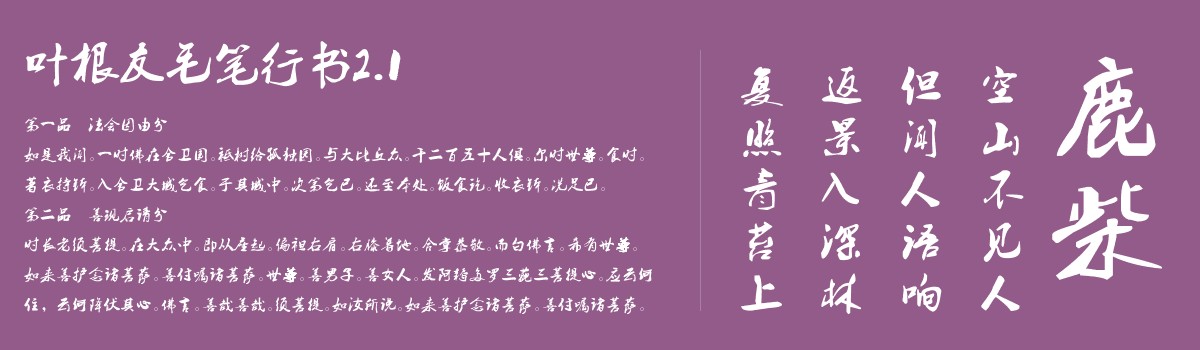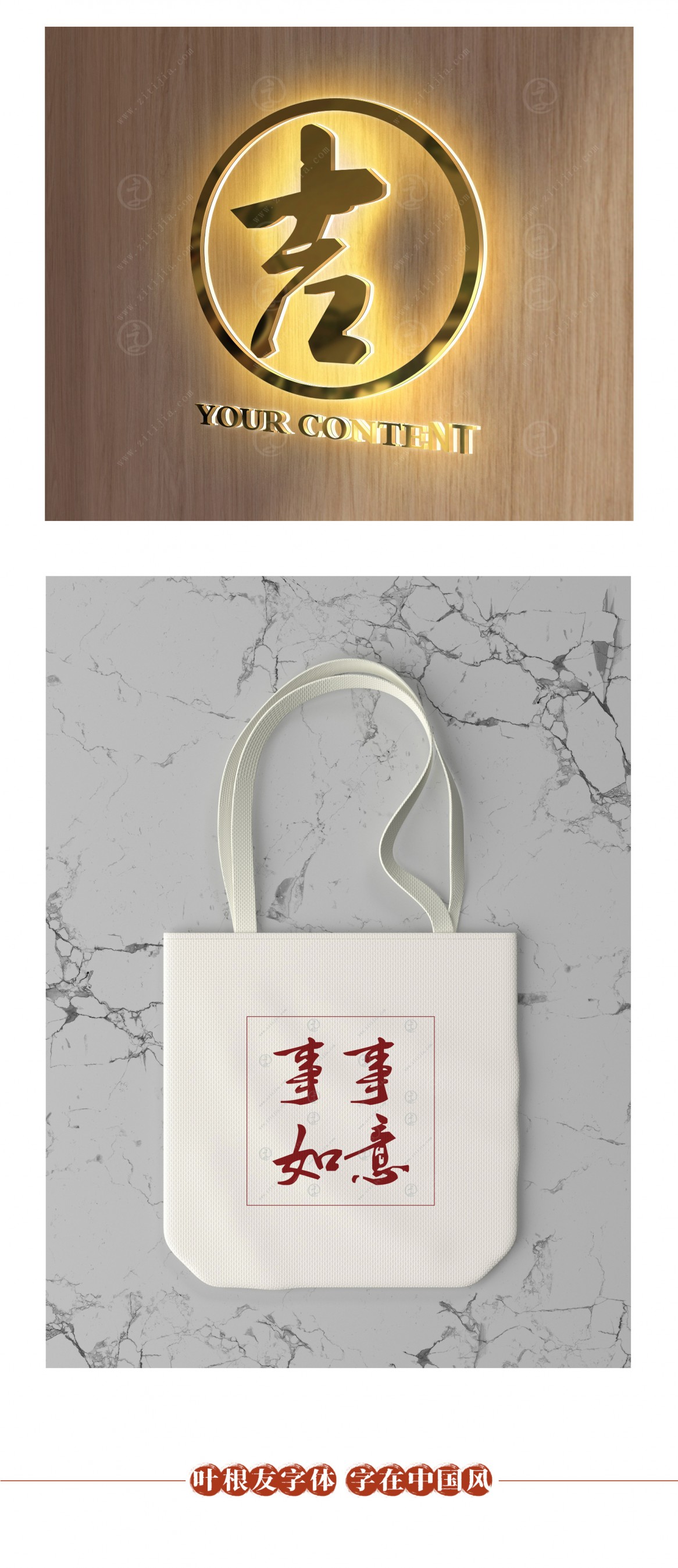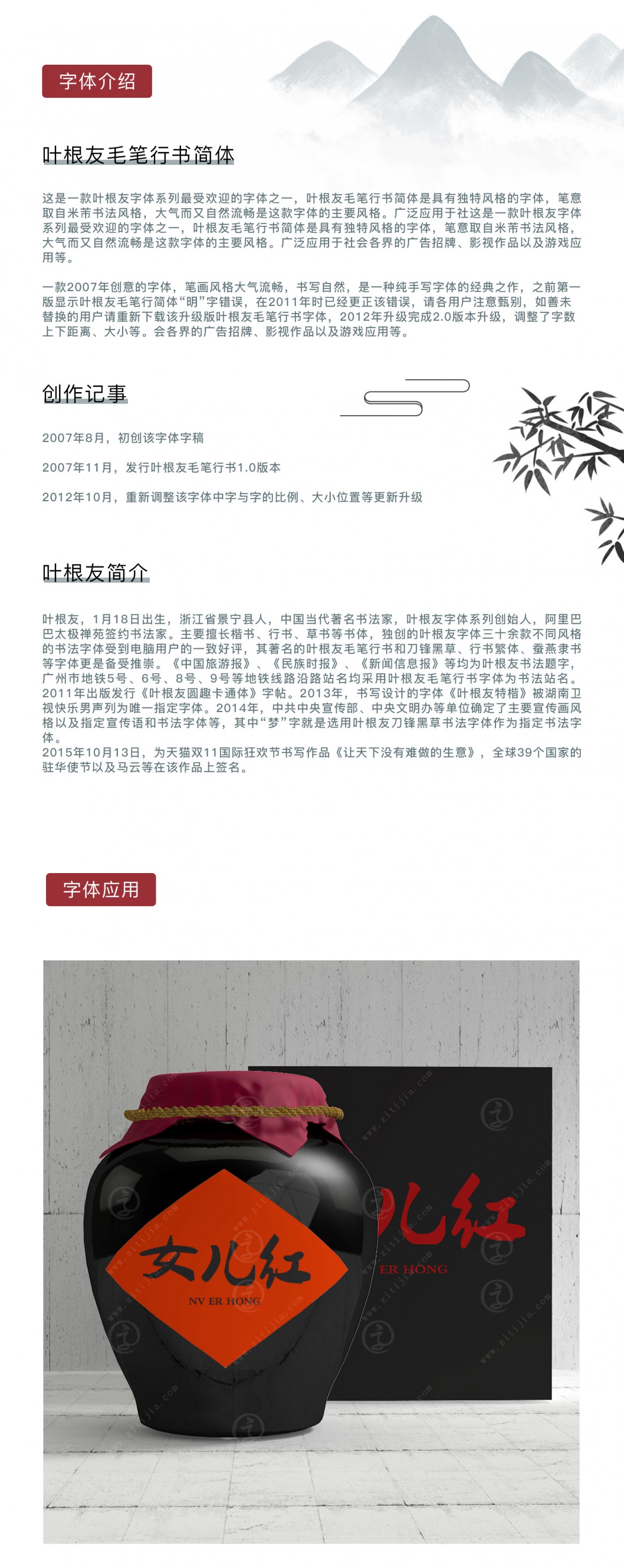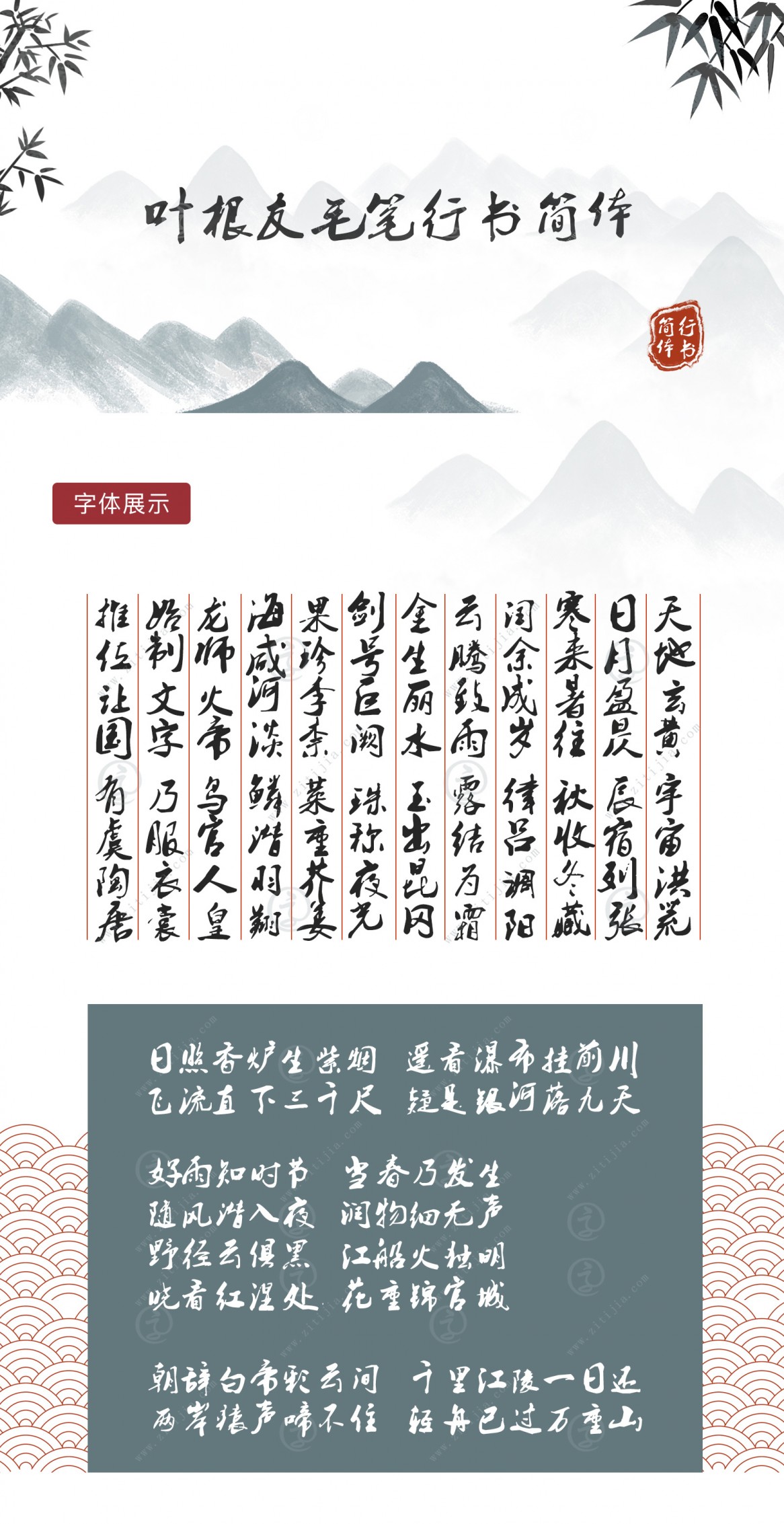
叶根友毛笔行书简体
字体作者:叶根友
创作年代:2007年
字体字数:6763个中文汉字以及其他英文字母和阿拉伯数字
字体介绍
这是一款叶根友字体系列最受欢迎的字体之一,叶根友毛笔行书简体是具有独特风格的字体,笔意取自米芾书法风格,大气而又自然流畅是这款字体的主要风格。广泛应用于社会各界的广告招牌、影视作品以及游戏应用等。
一款2007年创意的字体,笔画风格大气流畅,书写自然,是一种纯手写字体的经典之作,之前第一版显示叶根友毛笔行简体“明”字错误,在2011年时已经更正该错误,请各用户注意甄别,如善未替换的用户请重新下载该升级版叶根友毛笔行书字体,2012年升级完成2.0版本升级,调整了字数上下距离、大小等。
创作记事
2007年8月,初创该字体字稿
2007年11月,发行叶根友毛笔行书1.0版本
2012年10月,重新调整该字体中字与字的比例、大小位置等更新升级
2020年1月,重新调整部分字型以及修正苹果电脑系统不兼容问题